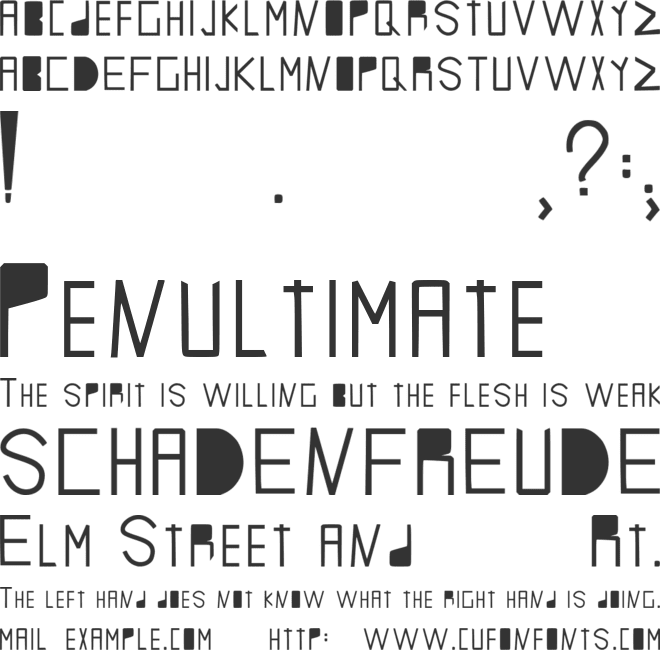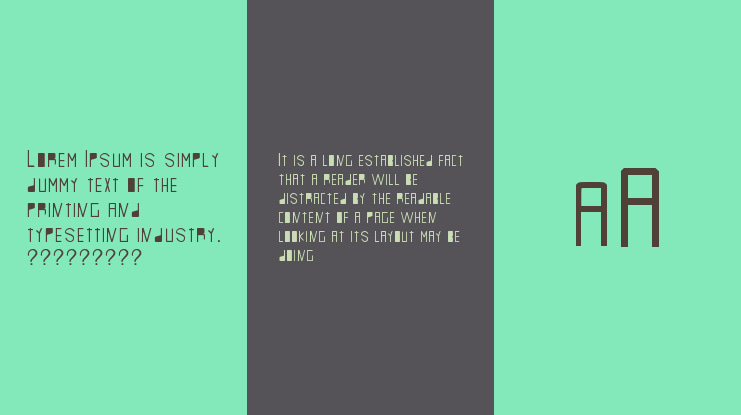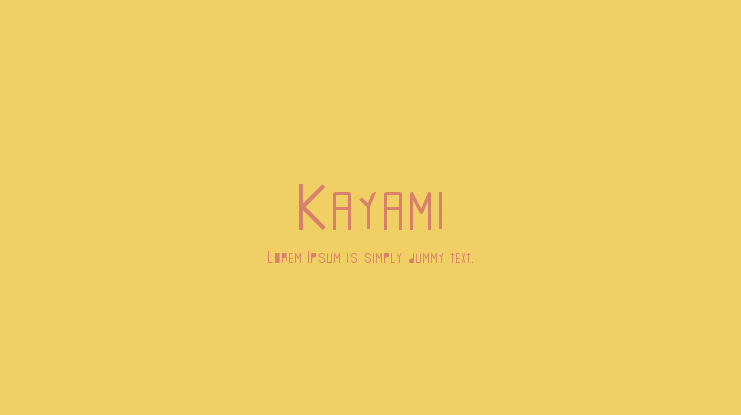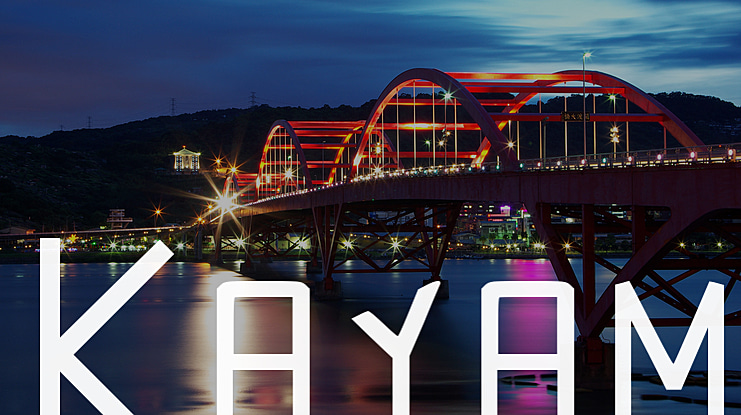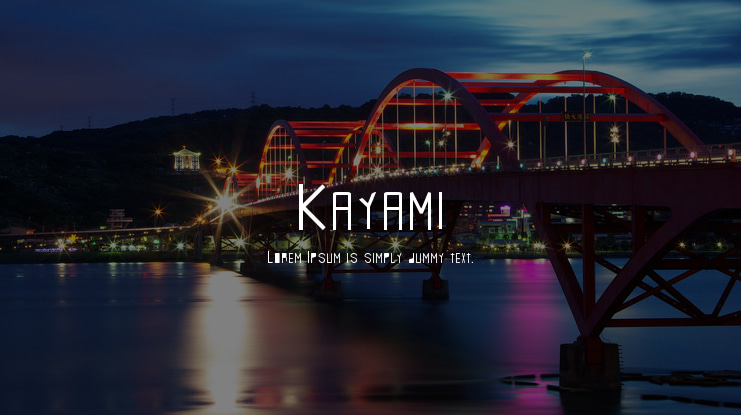
Kayami Font
Projeto desenvolvido na disciplina de Tipografia, das Faculdades Integradas de Bauru - FIB. O objetivo deste projeto era desenvolver uma fonte completa e original e aplicá-la em um folder não convencional. A inspiração da fonte e do folder teve origem no origami, pois este tema sempre me fascinou, e foi o começo do meu interesse por design. A fonte tem característica não serifada e lembra dobras e recortes que os origamis arquitetônicos tem, ela é composta de caixa alta e baixa e caracteres especiais, como ponto, ponto e virgula, acentos, pontos de exclamação e interrogação mas a fonte não contém “ç”. Mantive o aspecto minimalista pois queria que ela continuasse usável em outros projetos. Obrigada! Aproveitem!
Project developed in the discipline of Typography, from Faculdades Integradas de Bauru - FIB - Brazil. The aim of this project was to develop a complete and original font and apply it to an unconventional folder. The inspiration for the font and the folder originated from origami, as this theme has always fascinated me, and it was the beginning of my interest in design. The font has a non-serif characteristic and resembles folds and cutouts that architectural origami has, it is composed of upper and lower case and special characters, such as semicolon, accents, exclamation and question marks. I kept the minimalist aspect because I wanted it to remain usable in other projects. Thank you! Enjoy!
Kayami font preview